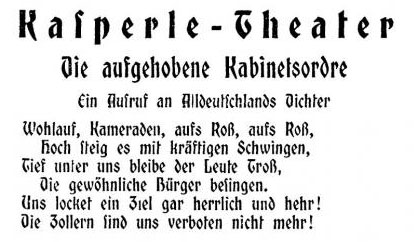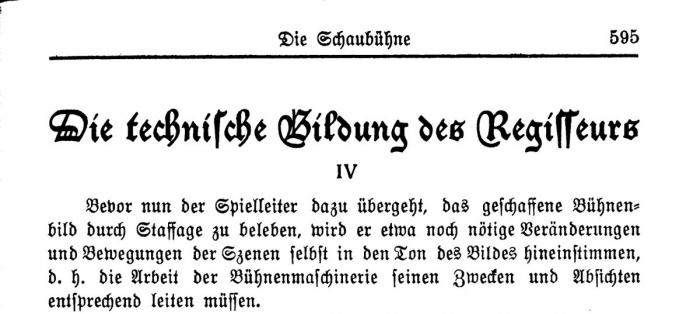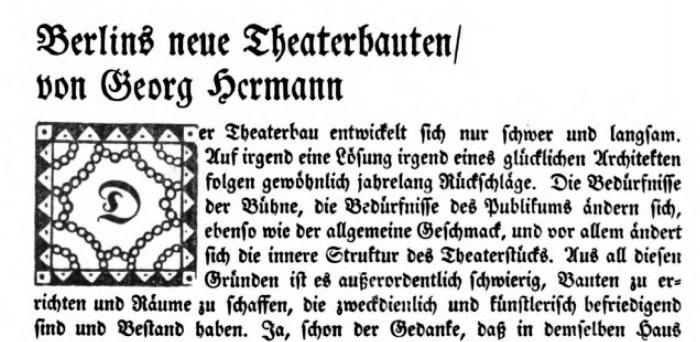
Typenwechsel in der "Schaubühne" 1906/07 - Welche Fraktur ist das?
"Die Schaubühne. Wochenschrift für die gesamten Interessen des Theaters", hrsg. von Siegfried Jacobsohn, wechselte zum Jahreswechsel 1906/07 die Druckerei (bis Dez. 1906 Buchdruckerei Wilhelm R. Saling & Co., Berlin SW. 13, Hollmannstr. 10, zu Imberg & Lesson, Berlin W. [Köthenerstr. 44], die ab Jan. 1907 die Hefte druckte). Damit verbunden war auch ein Wechsel der Drucktypen. Bis Dez. 1906 wurde mit mindestens zwei unterschiedlichen Typen gedruckt: (1)post-25850-0-16923400-1395997522_thumb.j und (2) post-25850-0-99648800-1395997545_thumb.j, ab Jan. 1907 mit (3) post-25850-0-21982800-1395997499_thumb.j . Leider ist es mir bisher gelungen, die "alten" und "neuen" Typen mit Namen zu identifizieren. Kann jemand helfen?
Hierbei handelt es sich um eine der zahlreichen
deutschen Nachahmungen der amerikanischen Bradley,
z.B.
Altgotisch, Amerikanische
Bauersche Gießerei, Frankfurt am Main, ca. 1908
oder
Alt-Gothisch
Berthold, Berlin, um 1900
oder
Britania-Gotisch
Julius Klinkhardt, Leipzig
oder
Britannia-Gotisch, Fette
Bauersche Gießerei, Frankfurt am Main, ca. 1908
Weitere Variationen siehe hier:
Vielen Dank boernie, auch für den Link. Vielleicht erkennt noch jemand ganz spontan die anderen zwei Typen. Könnte Nr. 3 eine "Weiß-Fraktur" sein?
Die Vorlage ist zwar nicht besonders gut,
aber es dürfte sich um folgende Schrift handeln:
Fraktur, Alte
Hausschnitt
Genzsch & Heyse, Hamburg, ca. 1906
Das ist eindeutig die
Angelsächsisch
AG für Schriftgießerei, Offenbach
Noch eine Ergänzung zur Schrift »Alte Fraktur« von Genzsch & Heyse, Hamburg:
Es gab zwei Schnitte, No. 1 und No. 2. Ich vermute, einen normalen und einen
halbfetten Schnitt. Mir steht aber nur die nachfolgende Abbildung zur Verfügung.
Besonders die Form des Versal-G legt die Vermutung nahe, das es sich bei deinem
Beispiel tatsächlich um die »Alte Fraktur« handelt.
Vielleicht kann jemand aus dem Forum Abbildungen beider Schnitte beisteuern.